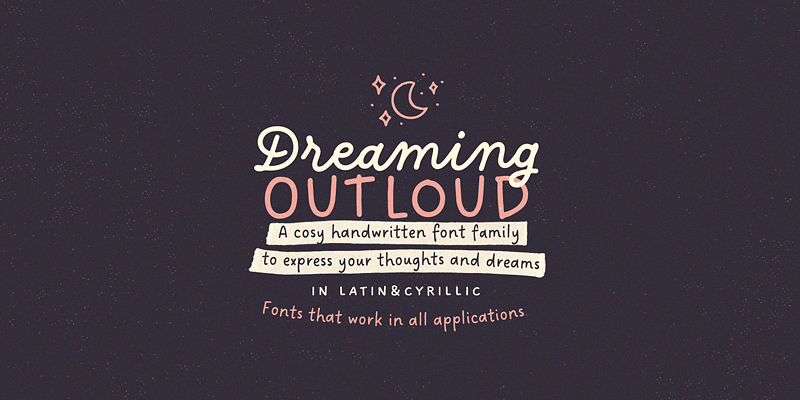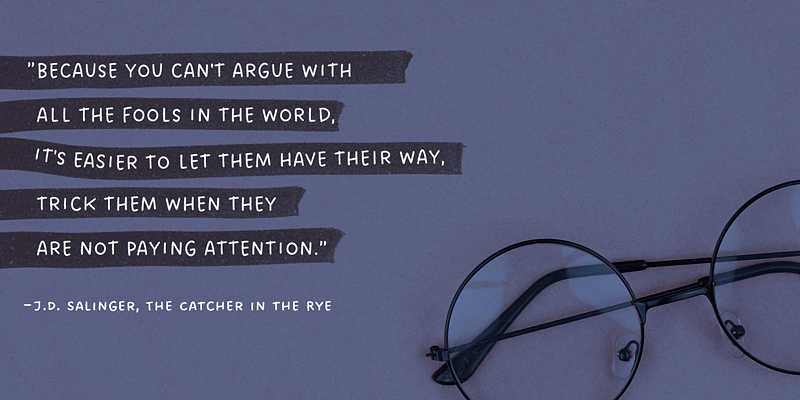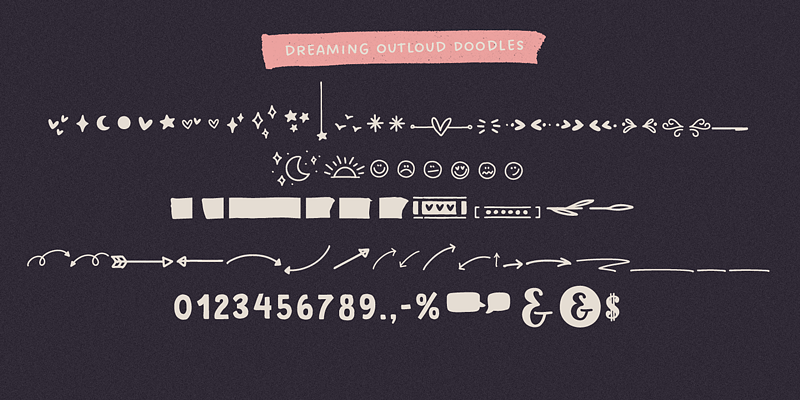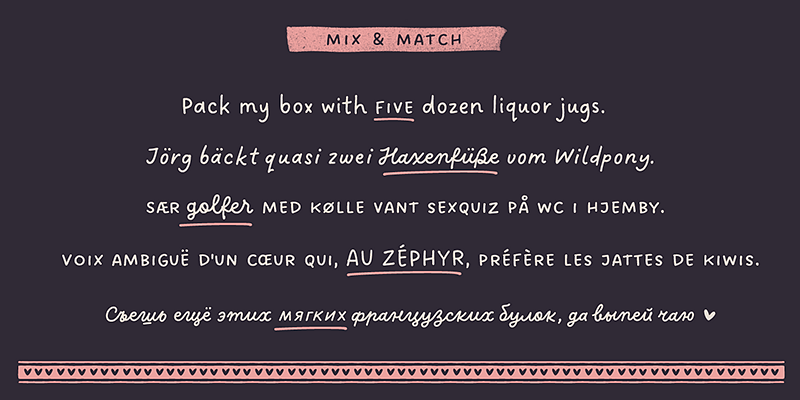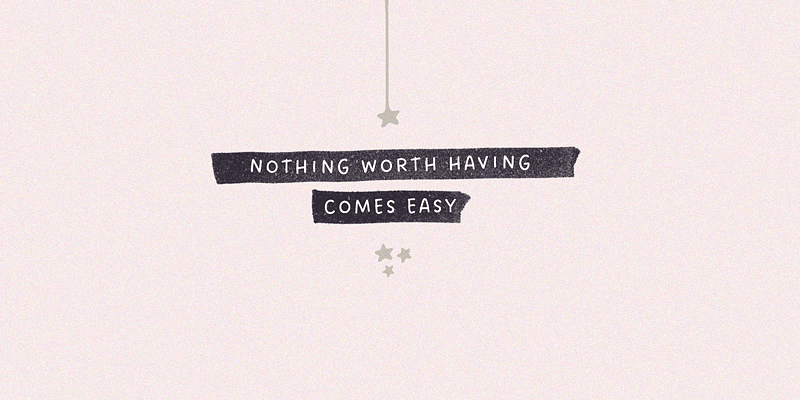
My Creative Land ist die Heimat der wunderschön handgefertigten Schriften von Elena Genova. Mit einer unerschütterlichen Hingabe an die Kunst der Buchstabenformen gehen die Schriften über das Gewöhnliche hinaus und vermitteln Emotionen, Tiefe und Einzigartigkeit im Design. Jede Schriftfamilie ist handwerklich sorgfältig ausgearbeitet und lässt sich oft direkt von der Schönheit von Kalligraphie und Handschriften inspirieren. Anspruchsvolle Designer werden wissen, dass My Creative Land über Schriften verfügt, die ihren Arbeiten das gewisse Etwas verleihen und ihre Ideen hervorheben.